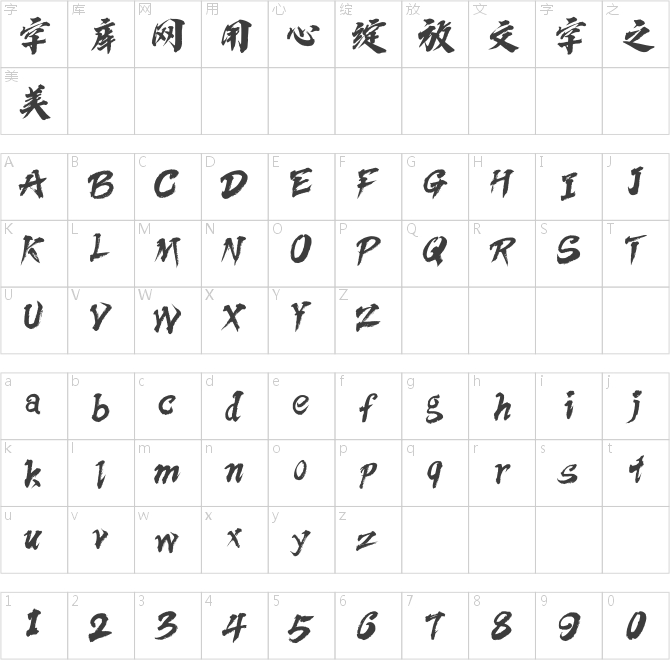
方正字跡-依然俠風(fēng)體
方正字跡-依然俠風(fēng)體字體FZZJ-YRXFTJW字庫是一款讓人賞心悅目、百看不厭的中文字體,適合各類廣告和產(chǎn)品包裝設(shè)計應(yīng)用,字體大小21.16MB,格式為TTF字體,上傳用戶是M_墨董,作者/版權(quán)方為方正字跡